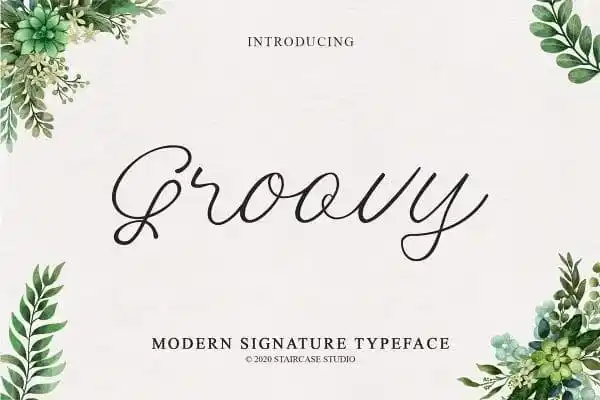
Groovy Script Font – Fonte Grátis
Groovy Script Font
A Groovy Script Font é uma elegante tipografia desenhada à mão com toques de mágica. Desenvolvida pelo Staircase Studio, essa fonte apresenta um estilo vintage ornamental com muitos swashes, permitindo que você crie cabeçalhos realistas com facilidade. Perfeita para postais de casamento ou logotipos únicos e originais, a Groovy Script Font também é perfeita para blog, cartões de aniversário, marketing e revistas. Ela oferece um tom criativo que vai muito além da simples escrita clássica, tornando-a uma escolha versátil tanto para designers quanto para amantes do design.